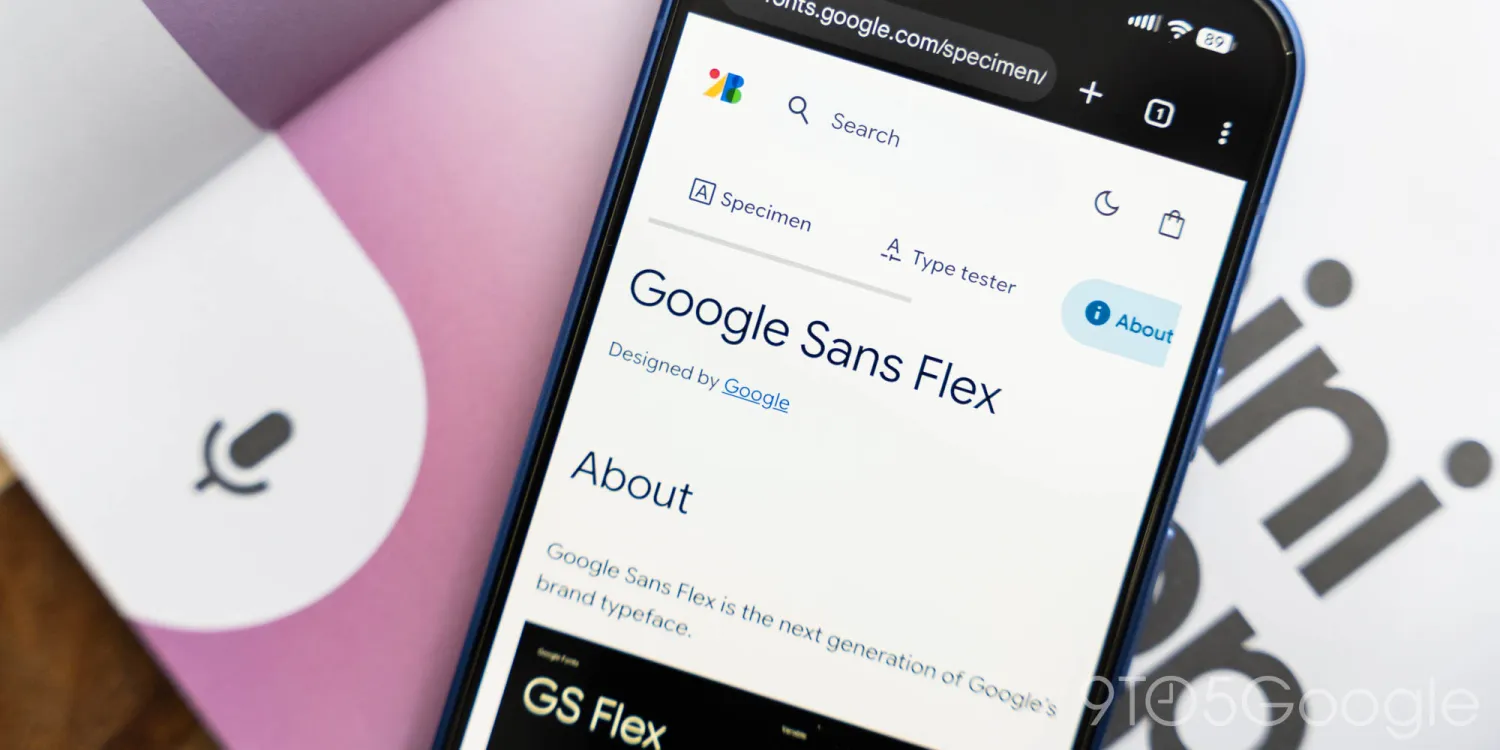
گوگل فونت Google Sans Flex را برای همه منتشر کرد
شرکت گوگل انتشار عمومی رایگان فونت Google Sans Flex را آغاز کرده است و طراحان و توسعه‌دهندگان می‌توانند از آن در پروژه‌های خود استفاده کنند.
به گزارش سرویس نرم افزار تک‌ناک، این فونت برای سال‌ها در محصولات مختلف این شرکت مورد استفاده قرار می‌گرفت و اکنون هر کاربر می‌تواند آن را از طریق وب‌سایت Google Fonts دانلود و استفاده کند. انتشار رایگان این فونت به توسعه‌دهندگان، طراحان و کاربران عادی اجازه می‌دهد تا همان هویت بصری مورد استفاده در اکوسیستم گوگل را در پروژه‌های خود به‌کار بگیرند.
فونت Google Sans Flex یکی از مهم‌ترین فونت‌های برند گوگل محسوب می‌شود و در بخش‌هایی از رابط کاربری گوشی‌های Pixel نیز دیده می‌شود. علاوه بر این، نسخه “Rounded” در چارچوب Material 3 Expressive بر پایه همین فونت طراحی شده است. این فونت نخستین‌بار در سال 2023 معرفی شد و اکنون به‌ عنوان بخشی از تلاش گوگل برای یکپارچه‌سازی زبان طراحی محصولات خود، به شکل عمومی و آزاد عرضه شده است.
شرکت گوگل در توضیحات رسمی اعلام کرده است که فونت Google Sans Flex نسل جدید تایپ‌فیس برند گوگل است. این شرکت تأکید کرد که ویژگی متمایز این فونت، توانایی تغییر فرم حروف در مقیاس‌های مختلف است؛ قابلیتی که آن را برای استفاده در طیف گسترده‌ای از نمایشگرها و کاربردهای طراحی مناسب می‌کند.
انتشار عمومی فونت Google Sans Flex گوگل آغاز شد